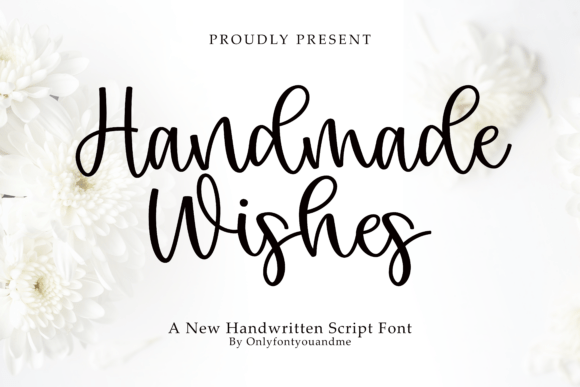
Handmade Wishes
適切なデザイン要素を見つけるのは難しい場合がありますが、Handmade Wishesは作品を即座に引き立てる優れたコレクションを提供します。
POD(オンデマンド印刷)製品、結婚式の招待状、またはソーシャルメディアのグラフィックを作成している場合でも、Handmade Wishesは理想的です。